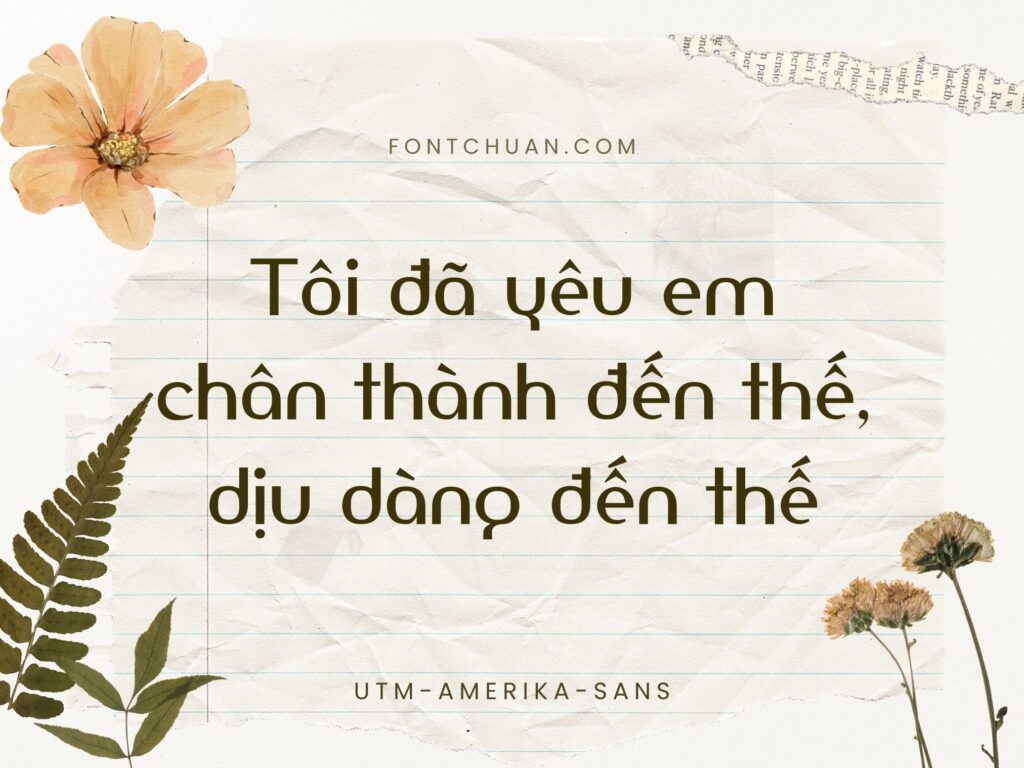
UTM Amerika Sans là một kiểu chữ sans-serif hiện đại được phát triển bởi Apostrophic Labs và phát hành lần đầu vào năm 2001. Font mang phong cách tối giản, gọn gàng và dễ đọc, phù hợp với nhiều mục đích sử dụng từ in ấn đến trình bày kỹ thuật số. Phiên bản Việt hóa được thực hiện bởi Đinh Kiên, hỗ trợ đầy đủ tiếng Việt cùng hơn 200 ngôn ngữ khác. Đây là một trong những font được thành viên Font Chuẩn sưu tầm và chọn lọc để phục vụ cộng đồng thiết kế trong các dự án đề cao sự rõ ràng, chuyên nghiệp và hiện đại.
UTM Amerika Sans sở hữu các nét chữ đều, không chân, với độ rộng ổn định và hình dạng cân đối, giúp tối ưu hóa khả năng hiển thị ở nhiều kích cỡ khác nhau. Font rất thích hợp để ứng dụng trong các thiết kế logo, tiêu đề, danh thiếp, bao bì sản phẩm, hồ sơ công ty hoặc các ấn phẩm thương hiệu. Những ngành nghề như quảng cáo, giáo dục, công nghệ và bất động sản có thể tận dụng Amerika Sans để tạo nên sự tin cậy, thân thiện và hiệu quả trong truyền thông hình ảnh.